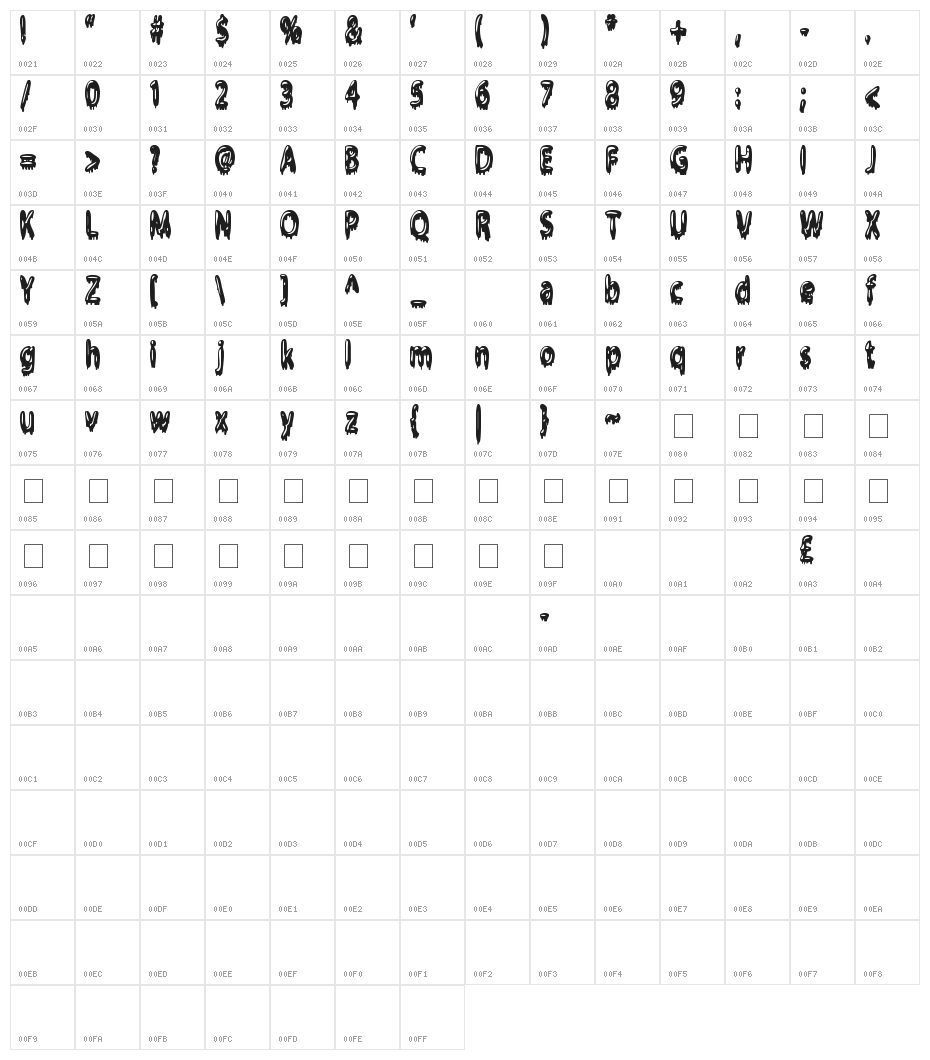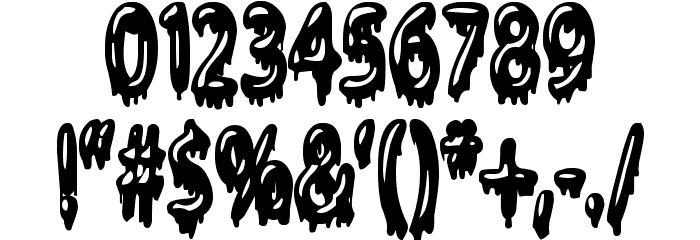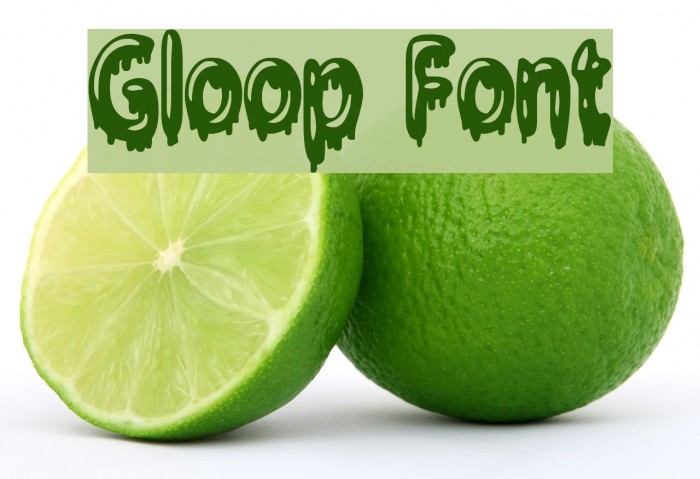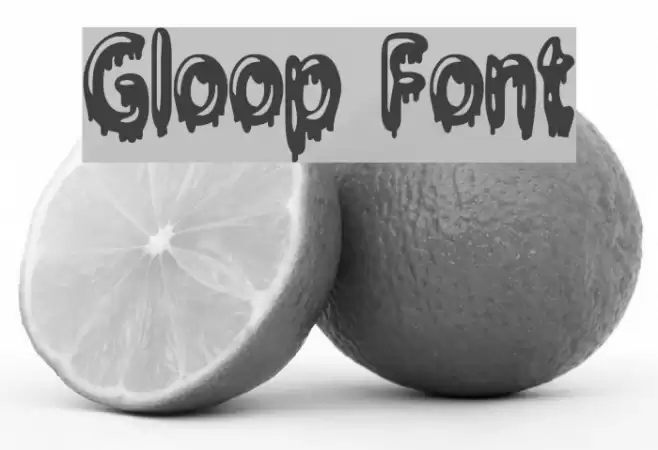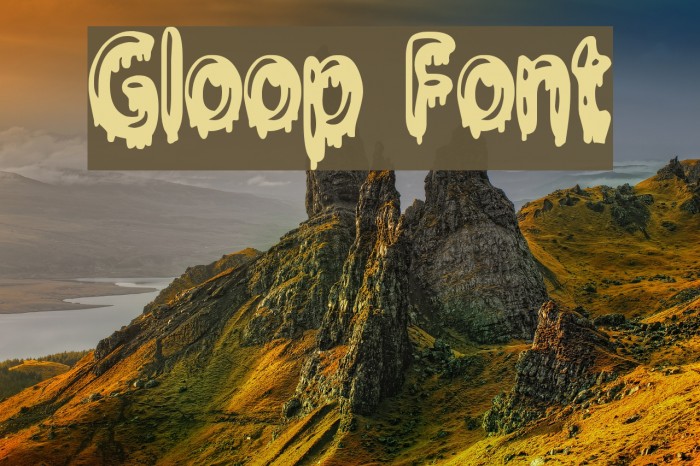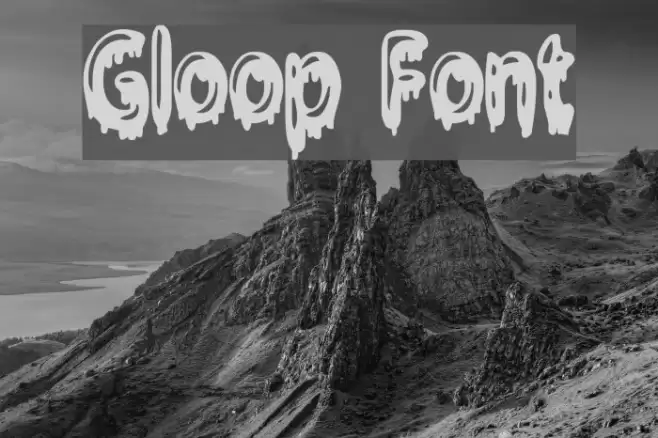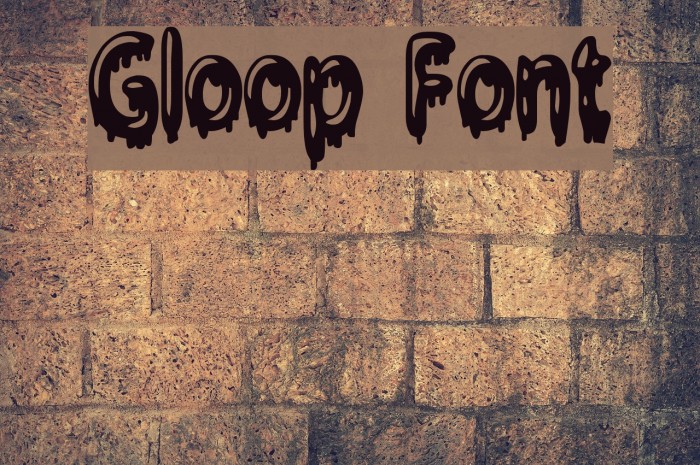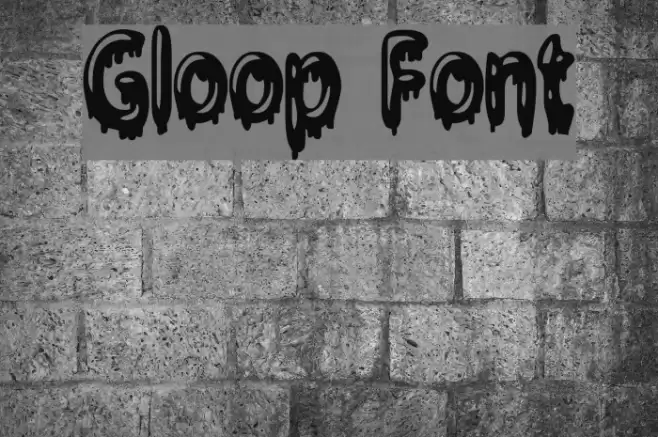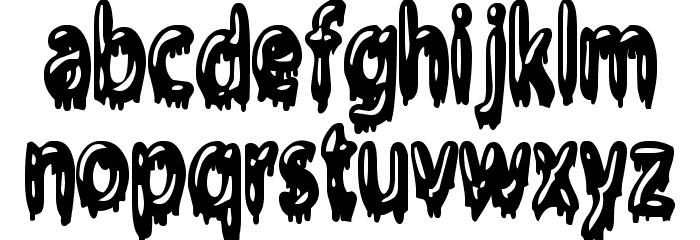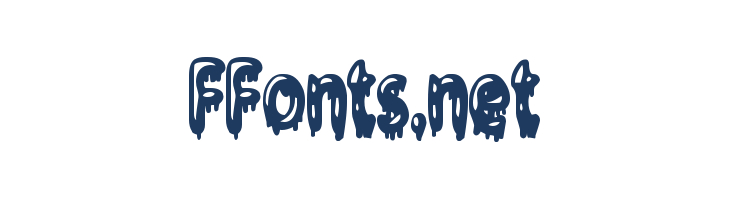
Gloop Font
✎ Horror
| Progetti proposti | Ideal for Halloween-themed designs, horror movie posters, children's party invitations, or any project needing a fun, spooky touch. |